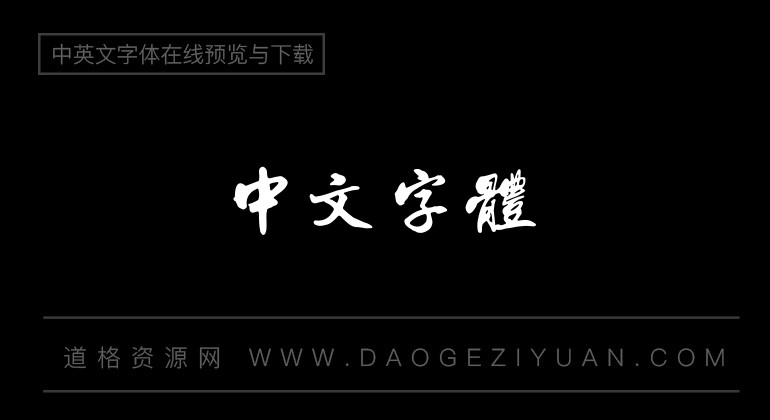
方圆孙中山行书
方圆孙中山行书是由孙中山先生所创作的一种行书字体,它以孙中山先生的名字命名,是以楷书为基础,在原有楷书的基础上,加入了一些自己的特色,使其具有较强的表现力和灵活性。方圆孙中山行书具有清新自然、流畅优美、大气洒脱、比例协调等特点。它的笔画比楷书更加圆润,比行书更加清新,比草书更加端庄,是一种比较完美的行书字体。
方圆孙中山行书是一款非常不错的手写艺术字体,具有很好的视觉感,适合于文化类的宣传设计、商业类品牌的广告和产品包装设计以及个性化文字排版等较多场景。